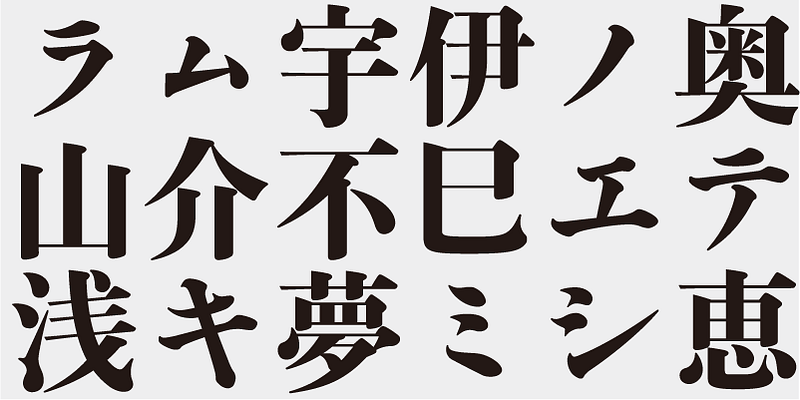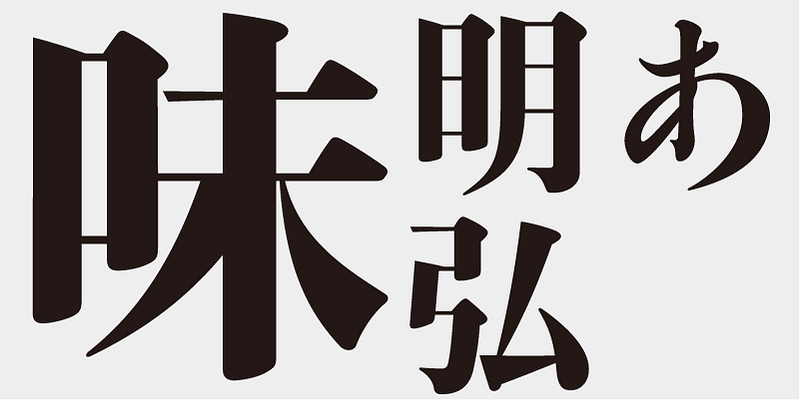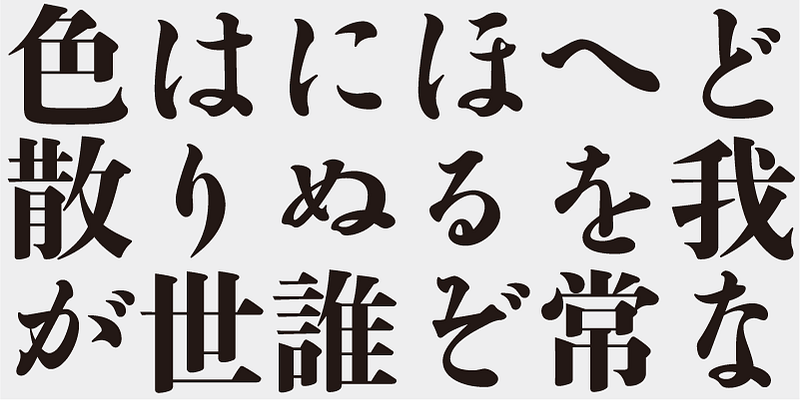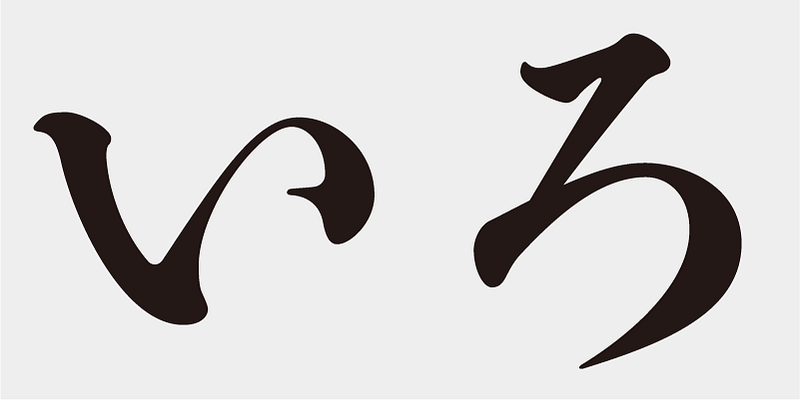
Bien qu’Ajimin épouse le style des caractères métalliques chauds, il n’est pas destiné à être un renouveau ; il s’agit plutôt d’une nouvelle police de caractères à des fins d’affichage. Tout comme Bodoni, ses traits verticaux sont nets et lourds et ses traits horizontaux sont précis et fins. Ses éléments traduisent la force et la stabilité.
Cette police est conçue pour être utilisée dans des tailles de caractères plus grandes (pour des affiches, par exemple), bien qu’elle soit lisible dans des formats plus petits. À mesure que la taille des caractères augmente, l’élégance de chaque élément de trait devient plus visible.
Selon les archives historiques, la police de caractères Koudouken-Shincho-tai a été créée au début de la période Meiji, lorsque Masayoshi Kanzaki a eu l’idée de créer une police d’écriture au pinceau ; le calligraphe Shouzan Komuro a écrit les caractères et Munenori Oyamada a gravé les poinçons en acier.
La conception était forte et masculine et elle est considérée comme l’un des plus grands chefs-d’œuvre de la conception de caractères japonais en métal chaud. Au fil du temps, ce caractère a été moins utilisé. En 1984, j’ai essayé de faire revivre sa structure de forme de lettre dans le style Mincho et j’ai publié le caractère Koudouken kana comme l’un des Ajioka Shintaro Kana Series pour la photocomposition. Je l’ai redessiné à nouveau comme Ajimin Ko/EB, en utilisant les caractères kanji d’Ajimin
Cette police comprend les 1 000 premiers caractères kanji choisis dans les tables de fréquence des caractères créés par les sociétés de presse, les maisons d’édition et les instituts de recherche linguistique, ainsi que 206 caractères kana et signes de ponctuation.
Ajimin a la saveur du caractère métallique chaud et, comme Bodoni, ses traits verticaux sont nets et lourds tandis que ses traits horizontaux sont fins et précis. Ses éléments dégagent force et stabilité. Ajimin est une police d’affichage unique de type Mincho. Les éléments Ajimin Modern sont conçus de manière plus nette et cette netteté contraste avec la richesse et l’élégance de la conception. Les atouts d’Ajimin sont ses 10 variantes kana, allant des conceptions manuelles à la renaissance de caractères métalliques chauds, en passant par le kana de style moderne. Grâce à ces variantes, les polices Ajimin conviennent à un grand nombre d’usages.